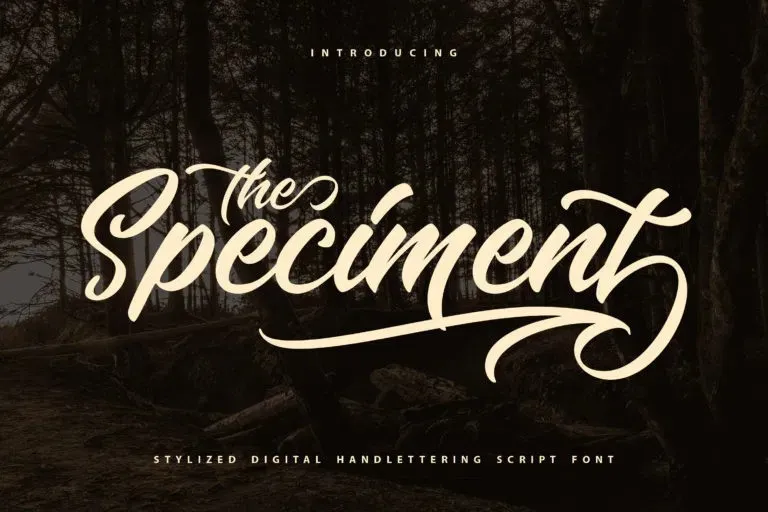
The Speciment Font – Fonte Grátis
The Speciment Font
A fonte ‘The Speciment Font’ é uma delícia para designers que buscam personalidade ao adicionar um toque delicado à sua criação. Essa script font, criada pela 99designs, apresenta linhas fluidas e caracteres atraentes perfeitos para complementar suas próximas projetos de design. Seja ela aplicada em design de casamento, logotipos, frases de apelo, postagens nas redes sociais ou conteúdo exibido nos vídeos – a ‘The Speciment Font’ é versátil e perfeitamente adaptável a diversos formatos. As imagens de pré-visualização mostram uma variação deliciosa do estilo da fonte que destaca seu poder em criar um design único e memorável. Ela traz um toque delicado e criativo sem abandonar a beleza essencial, perfeitamente adaptada para se tornar parte integrante de qualquer projeto visual. Com ‘The Speciment Font’, você pode capturar e transmitir uma mensagem especial de forma única e impactante.